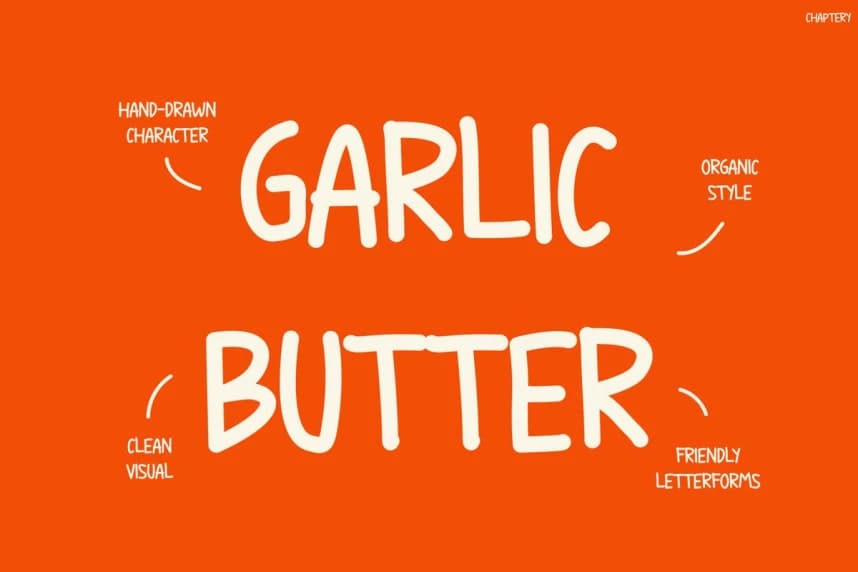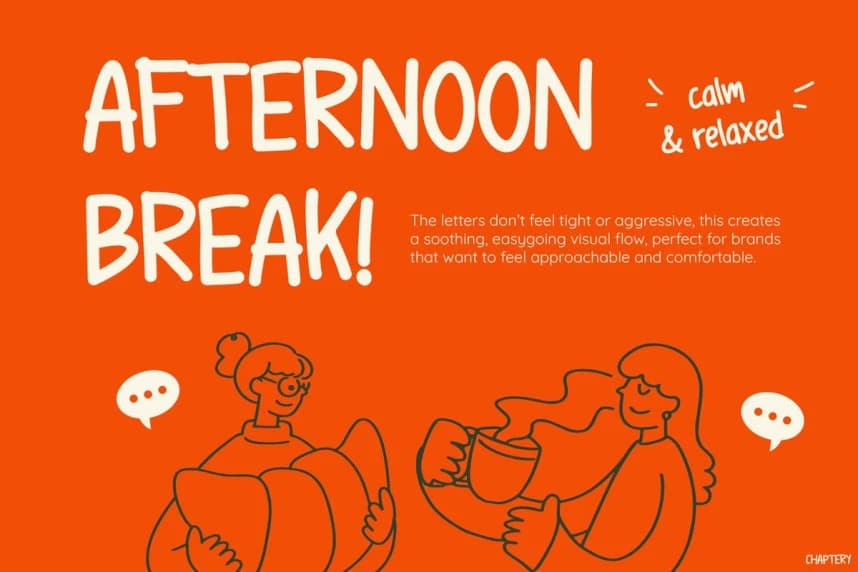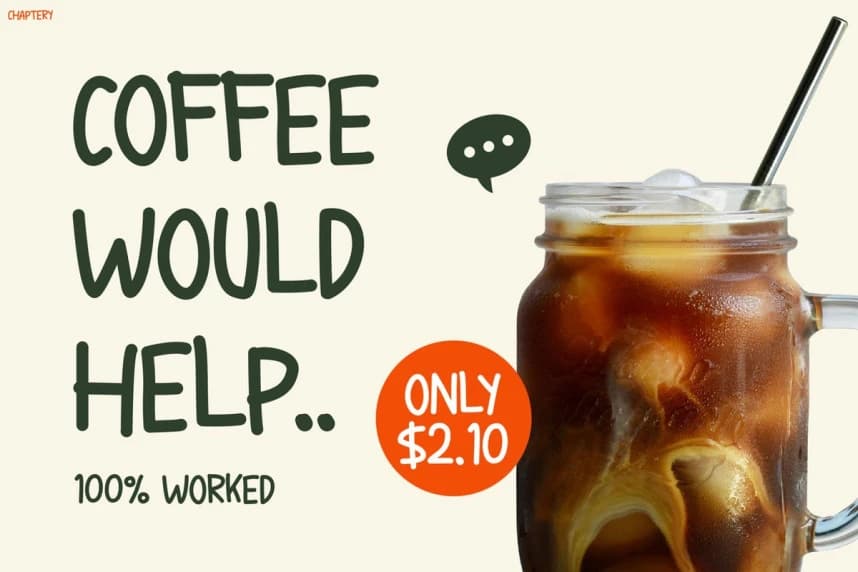
Chaptery Eğlenceli Yazı Tipi
Chaptery Playful Font, sıcak, el yazısı bir display yazı tipidir ve oyuncu çekiciliğini rahat, kafe esintili bir estetikle birleştirir. İlk bakışta, yumuşak eğrileri ve hafifçe düzensiz çizgileri hemen doğal, insan dokunuşu yaratır.
Chaptery Playful Font, sıcak, el yazısı görünümlü bir gösterim yazı tipi olup oyuncu çekiciliğini rahat, kafe temalı bir estetikle harmanlar. İlk bakışta, yumuşak eğrileri ve hafif düzensiz çizgileri hemen doğal, insani bir dokunuş yaratır.